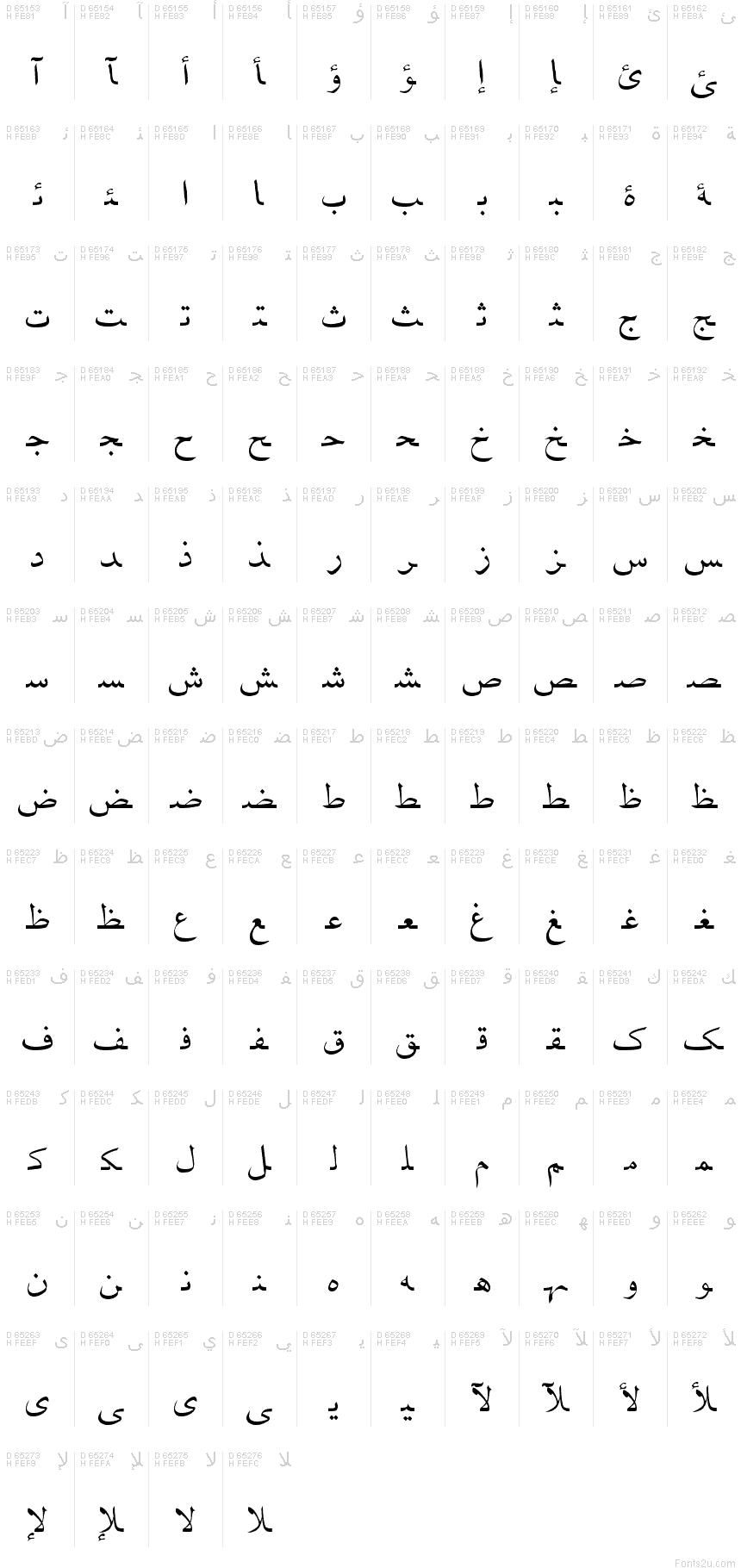
B Ferdosi, da Borna Rayaneh, é uma fonte caligráfica árabe gratuita com um ritmo compacto e fluido, ostentando um tom persa distintamente tradicional. As letras têm um toque de pincel em vez de serem geométricas, com curvas suaves, junções afinadas e um movimento levemente manuscrito que mantém a linha viva sem se tornar ornamental.
Adequa-se a capas de livros, cartazes culturais, títulos de poesia, gráficos de museus e cabeçalhos editoriais onde o clima clássico é mais importante que a neutralidade. Como fonte gratuita, também é uma excelente escolha para cartões de título curtos, nomes em embalagens e marcas de identidade que precisam de uma escrita árabe com calor e um caráter literário e tradicional.